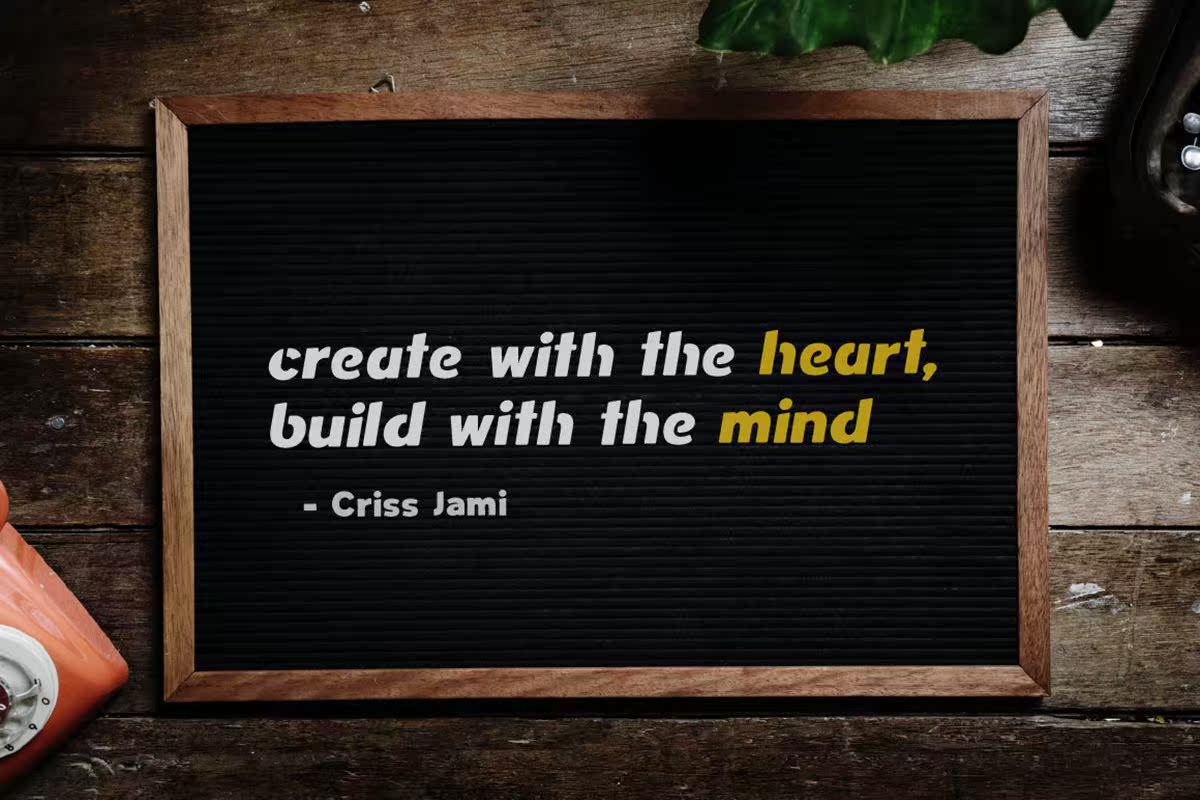
Spotlight Free Demosans在同一种Modern Sans Serief字体上进行设置。它适用于标题、徽标甚至连续文本。此字体具有漂亮的调制字体和平衡笔划宽度,您可以在常规字体和真实斜体之间进行选择。它具有特殊的Tencil样式,可赋予您指定的唯一外观。无论如何,尝试使用Free字体,或购买商业许可证以获得更多功能